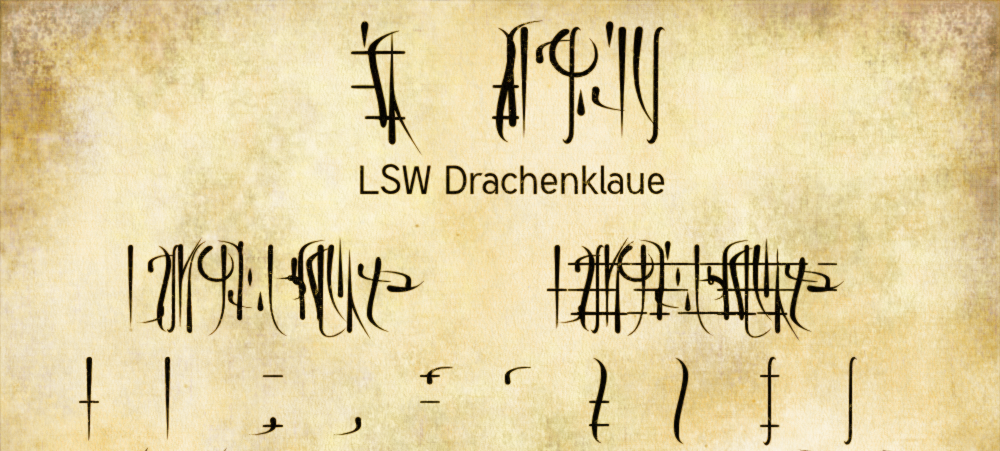
LSW Drachenklaue Font – Download Grátis
Aqui está uma descrição para a página de download da font ‘LSW Drachenklaue Font’ no idioma português do Brasil: Nossa nova adição é uma fonte que vai deixar seu projeto inovador e único, sem abrir mão de qualidade e precisão. Inspirada na mitologia medieval, essa fonte especial permite que você personalize textos de forma elegante, criando um ar arcaico em sua próxima criação gráfica. Criada por Hamilton, a LSW Drachenklaue Font oferece uma experiência única ao trabalhar com letras verdadeiras e fáceis de usar. Seu design diferenciado foi projetado para manter os aspectos clássicos e elegantes da fonte tradicional, enquanto também apresenta um toque moderno que o torna perfeitamente adaptável a diversas necessidades gráficas. Seja você designer ou ilustrador, estendendo seu conhecimento com novas ferramentas pode ser a chave para uma nova geração de projetos. A LSW Drachenklaue Font é mais um passo em direção à inovação do mundo da fonte, oferecendo aos criativos uma opção única e autêntica que combina o melhor dos tempos passados com as últimas tendências digitais.